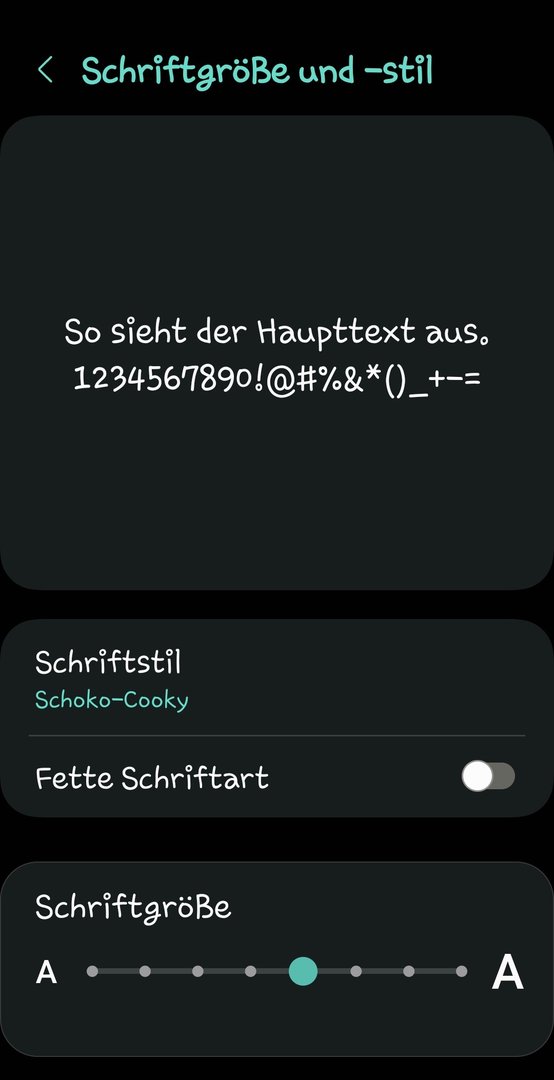
Welche Schriftart verwendet Ihr auf dem Galaxy S22 Ultra?
ich benutze seit einer Woche diese hier:
Vanilla Cream
Sie sieht in meinen Augen ein wenig wie die Google Font aus, klar und schnörkellos, aber trotzdem nicht so Standard.
Die hier wäre was für alle Retro-Enthusiasten😉:
Lomo
Die Schriftart Schoko-Cooky nutze ich gefühlt schon seit dem Note 1.
Schreibt sich die nicht Choco cooky,nur falls sie jemand sucht?
Also bei mir steht "Schoko-Cooky"
Ein Hoch auf die DEnglische Sprache 👏
Germania one
Die Schriftart Schoko-Cooky nutze ich gefühlt schon seit dem Note 1.
Die nutze ich auch schon immer und möglichst auf allen Smartphones. Sogar durch den schlimmen Xiaomi Theme Store habe ich mich dafür gekämpft. Und wurde auch fündig. Einfach die beste Schriftart.